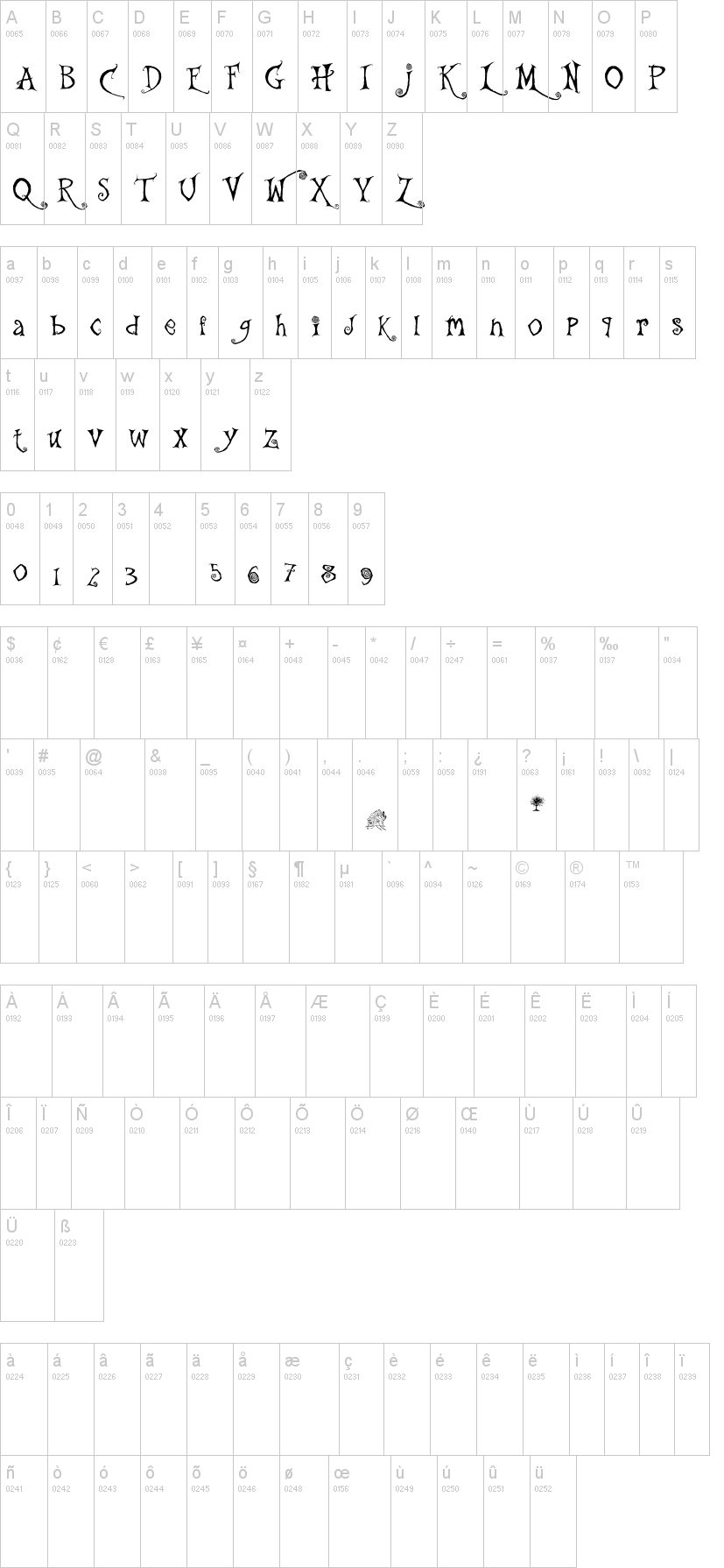
The Gingerbread House
The Gingerbread House字体是一款英文手写体字体,它的特点是具有柔和的线条,温暖的颜色,可以为您的设计带来浪漫的气息。字体的线条十分细腻,每个字母都具有独特的质感,可以营造出一种温暖友善的氛围。它可以用于创建浪漫的节日卡片,比如圣诞卡片,也可以用于婚礼邀请,婚礼请柬等。
The Gingerbread House是一款非常不错的手写艺术字体,具有很好的视觉感,适合于文化类的宣传设计、商业类品牌的广告和产品包装设计以及个性化文字排版等较多场景。